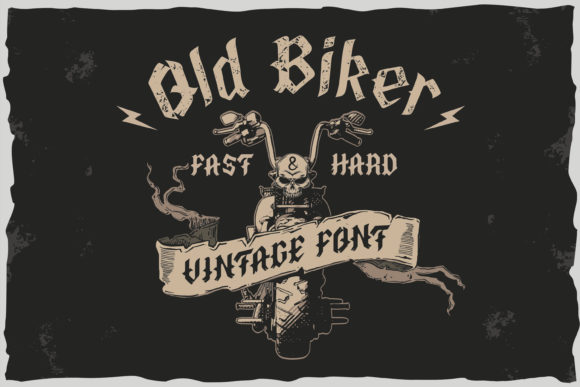
Old Biker
Découvrez Old Biker – La Police Old School Qui Donne Vie à Vos Projets
Vous cherchez une police qui allie audace, style vintage et impact visuel maximal ? Old Biker est la réponse. Cette police blackletter dramatique et assertive transformera instantanément vos créations, que vous conceviez un logo, une couverture de livre, une affiche ou une publication sur les réseaux sociaux.
Pourquoi Old Biker est le Choix Idéal pour Les Concepteurs
- Style vintage audacieux : Les formes old school et inspirées des motos donnent à chaque projet un attrait intemporel et rétro.
- Impact visuel dramatique : Sa taille imposante et sa présence assertive captent l'attention et renforcent le message.
- Encodage PUA : Accédez facilement à tous les glyphes et swashes exotiques pour une personnalisation sans limites.
- Adaptabilité exceptionnelle : Que ce soit en titre, en corps de texte ou en élément décoratif, Old Biker s'adapte parfaitement à toutes les dimensions.
Découvrez Ses Fonctionnalités Exceptionnelles
Old Biker n'est pas qu'une simple police ; c'est une boîte à outils complète pour les typographes. Grâce à son encodage PUA, vous pouvez exploiter une vaste gamme de glyphes alternatifs et de swashes complexes pour ajouter des touches décoratives et une personnalité distinctive à vos designs. Sa richesse en caractères inclut :
- Une large gamme de lettres majuscules et minuscules
- Des ligatures et des ornements alternatifs
- Des chiffres et des symboles uniques
- Des swashes étendus pour des signatures élégantes
Idées de Design avec Old Biker
Utilisez Old Biker pour :
- Logos emblématiques et identités de marque
- Affiches et titres de livres inspirés par l'esprit des motos
- Titres de articles et en-têtes de blogs pour capter l'attention
- Publications sur les réseaux sociaux et designs publicitaires percutants